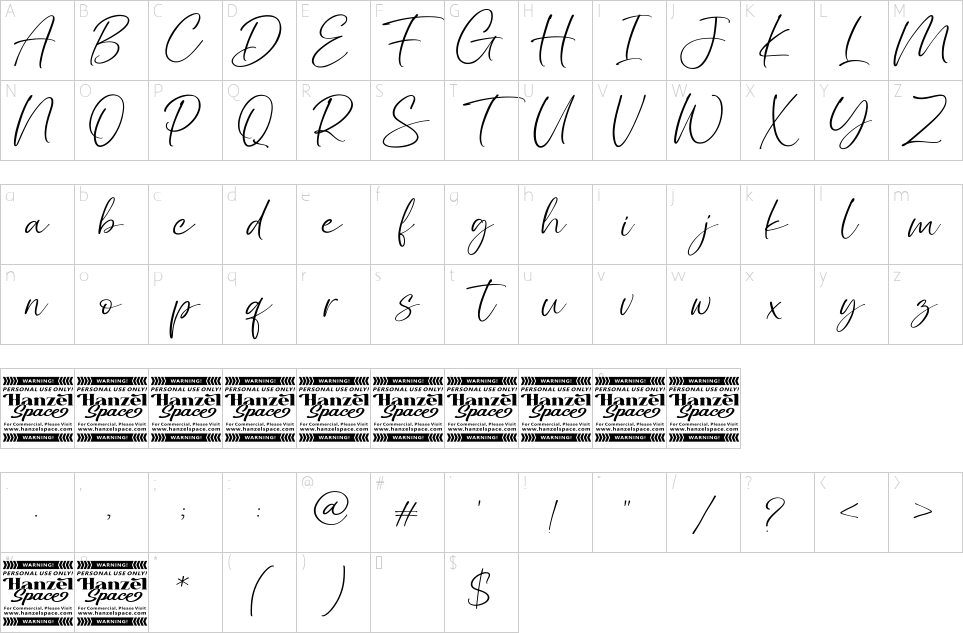
Jellovy Switch é uma elegante fonte que se destaca entre as demais por sua tipografia fluida e vibrante. Criada pelo produtivo Hanzel Space, ela traz um toque único para qualquer projeto digital, seja ele site, aplicativo ou material gráfico impresso. Esta fonte foi desenvolvida pensando em proporcionar uma experiência visual agradável e funcional, adaptada tanto para sistemas Windows quanto para Mac. Com seu design envolvente, Jellovy Switch é perfeita para quem busca se destacar através de um layout moderno e sofisticado. Em sua versão gratuita, você pode experimentar o poder desta fonte em seus projetos sem precisar pagar nada adicional. Desfrute das possibilidades criativas que a Jellovy Switch oferece!